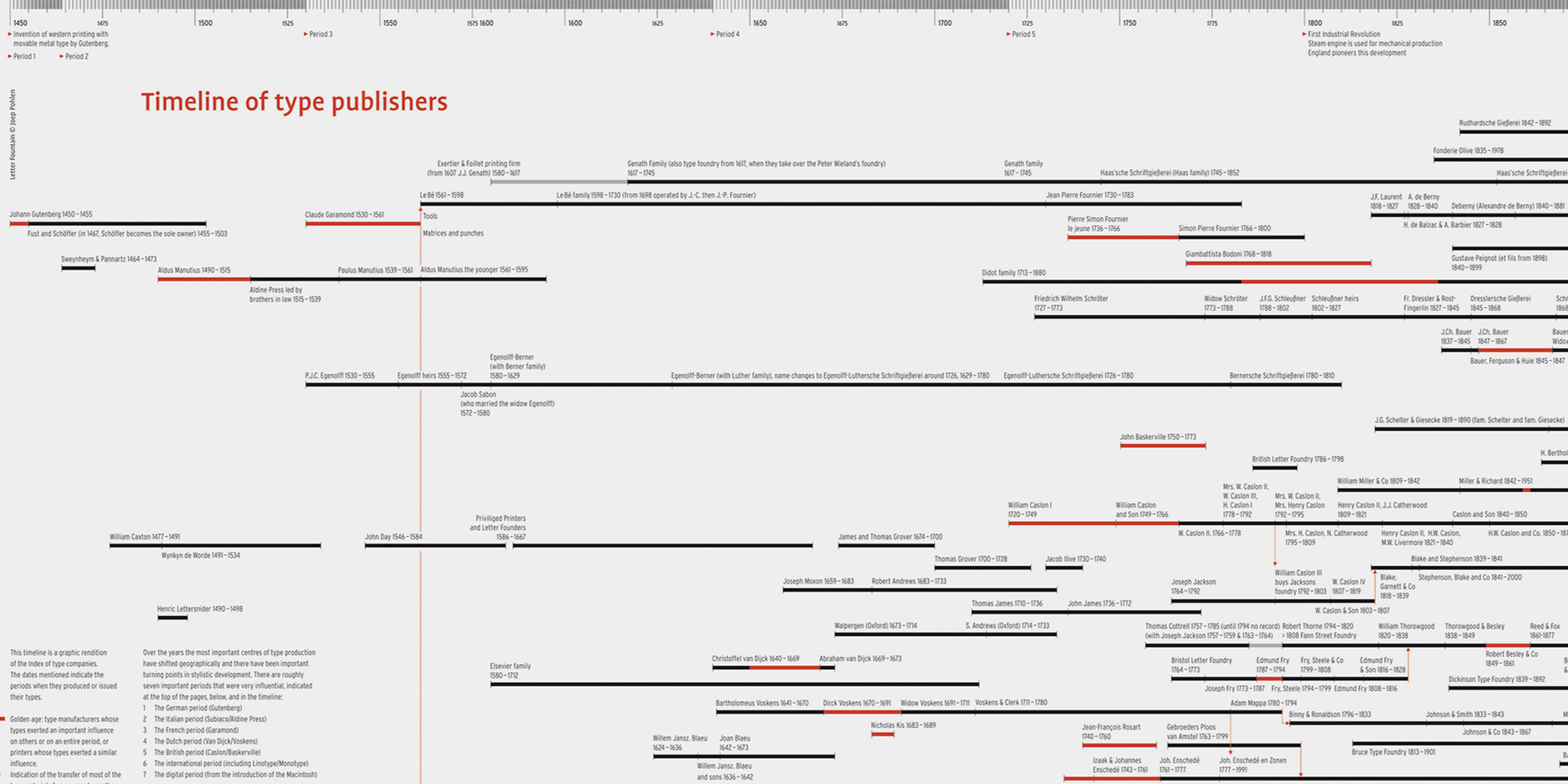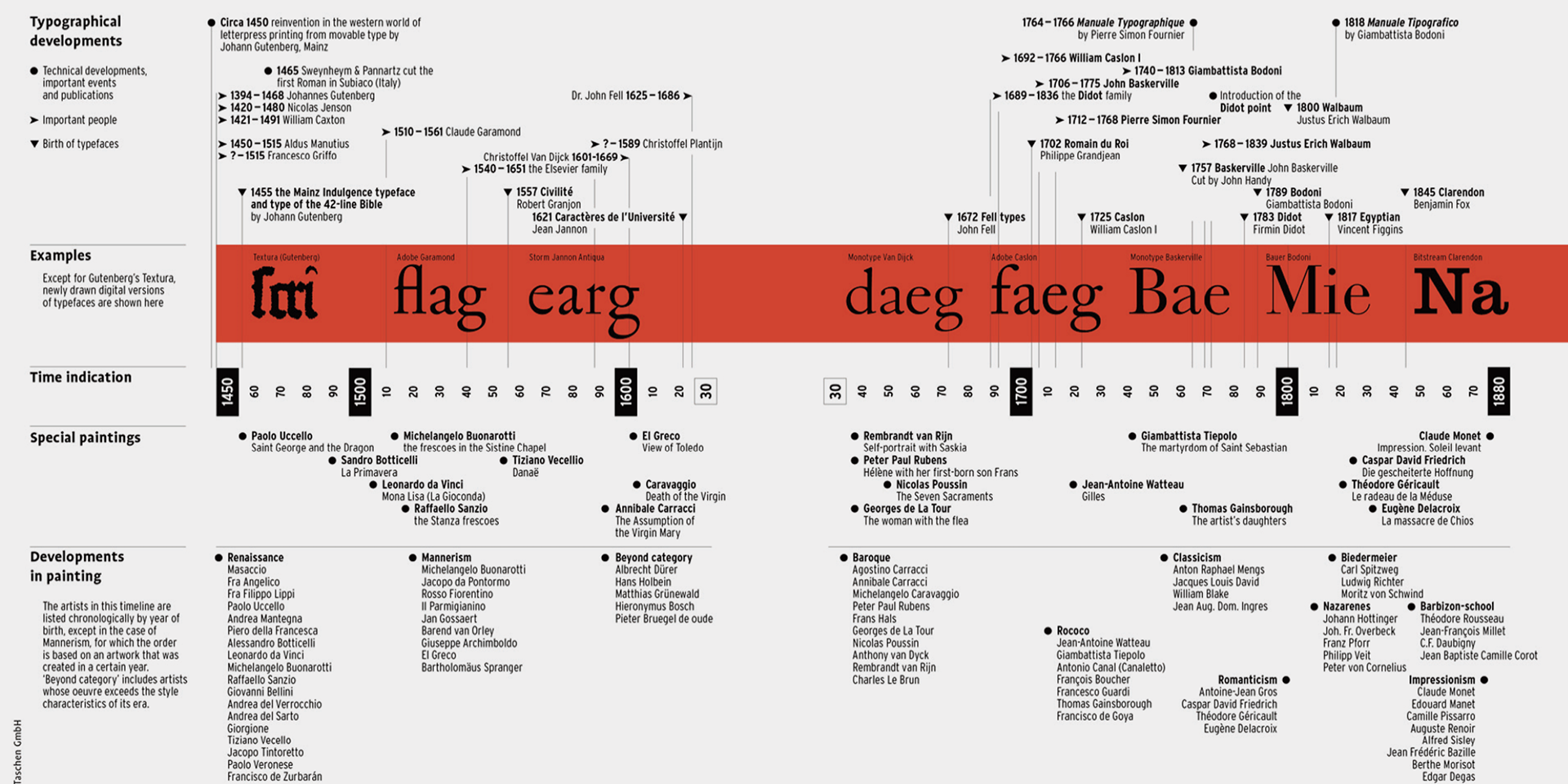
Zasoby internetowe
Podstrona zawiera wyselekcjonowane źródło internetowe, przydatne dla osób pragnących poszerzać swoją wiedzę dotyczącą typografii.
Domy typograficzne
Domy typograficznych (ang. type foundries) to niezależne firmy zajmujące się projektowaniem autorskich krojów pisma:
Na poniższych stronach znajdują się indeksy większości aktualnie działających domów typograficznych:
Wybrane przykłady domów typograficznych projektujących kroje wysokiej jakości, które warto poznać:
Polskie domy typograficzne:
Dystrybucja fontów
Platformy prowadzące sprzedaż fontów różnych projektantów i producentów:
Blogi o typografii
Historia typografii
Typoteka – platforma opisująca poszczególne etapy rozwoju polskiej typografii, zawiera indeks krojów pisma stworzonych przez twórców związanych z Polską.
Counterspace Typography Timeline – interaktywna oś czasu, prezentująca kluczowe wydarzenia z historii typografii
Typographical developments – wykres wyszczególnia znaczące
osiągnięcia w dziedzinie projektowania krojów pisma. Dodatkowo, zestawia te osiągnięcia z ewolucją historii sztuki i projektowania. Do pobrania w formie pliku pdf na stronie Letter Fountain.
Timeline of type publishers – wykres prezentujący wydawców, którzy
istotnie wpłynęli na rozwój dziedzin
projektowania krojów pisma i typografii. Do pobrania w formie pliku pdf na stronie Letter Fountain.